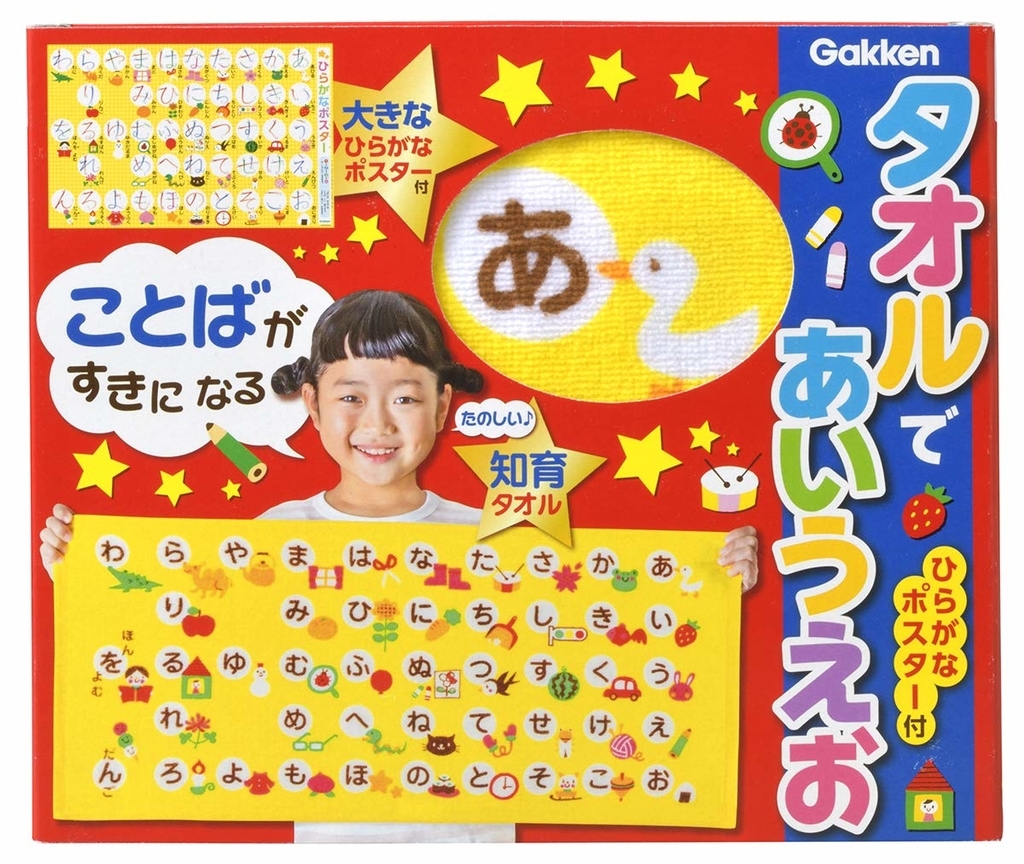
タオルであいうえお ひらがなポスター付
学研ホールディングスのグループ会社である学研教育みらいは、タオルで楽しくひらがなに触れ、ポスターで正しい書き順をマスターできる、マメリツコ氏がイラストを担当した「タオルであいうえお ひらがなポスター付」を2019年2月5日に発売した。
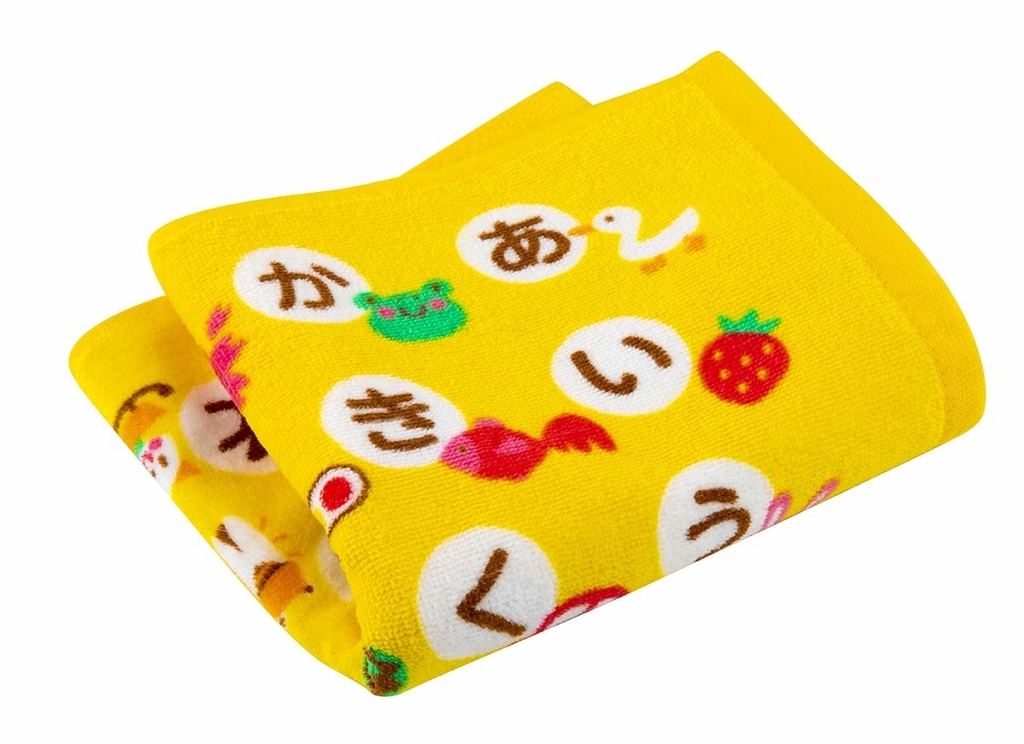
「タオルであいうえお ひらがなポスター付」は、小さい頃から親しんでおきたい平仮名が毎日使えるフェイスタオルで楽しく覚えることができる知育タオル。ふわふわの手触りでかわいいイラスト付きなので、お風呂、お昼寝、お出かけなど何処にでも持っていける、持っていきたいタオルになっている。
正しい書き順、とめ・はね・はらいが分かりやすい大きなひらがなポスター付きで、部屋に貼ることで、親子のコミュニケーションアイテムとして活用できる。
はじめて触れる平仮名として、入学準備の第一歩として、丈夫な箱入りでお誕生日のプレゼントとしても最適なタオル。
「そろそろ『あいうえお』を教えたい!」と感じた際、まず思いつくのは絵本やパズルあたりを考える事が多いと思うが、いきなり一人では使えないし、教え方もわからない、すぐ飽きちゃいそう…、散らかるのも嫌…というそんな心配指数MAXの不安な親御さんにピッタリなのが、いつでもどこでも毎日楽しく使える「タオル」。
お風呂の時はもちろん、お昼寝の時にお腹にかけるも良し!お出かけの時に持って行くも良し!「お風呂イヤ!」の子供もこのふわふわでかわいいタオルで「入る!」の一言が手に入るはず。また、「手洗いが面倒!」の子供にも「これなら使ってみたい!」の一言もきっと手に入るはず。
なかなか文字に興味が湧かなくて…と悩んでいるお父さんお母さんによる「入学準備」としても、タオルを使っている内に自然とひらがなに親しんでいけるスタイルでタオルに触れる内に楽しくひらがなにも触れ、ポスターで正しい書き順をマスターできる仕組みなのでオススメ。
また、タオルとポスターがセットになって丈夫な箱に入っているので、プレゼントにも最適。「かわいい」「使える」「役に立つ」+「学べる」贈り物で、喜ばれること間違いなしのタオルになっている。